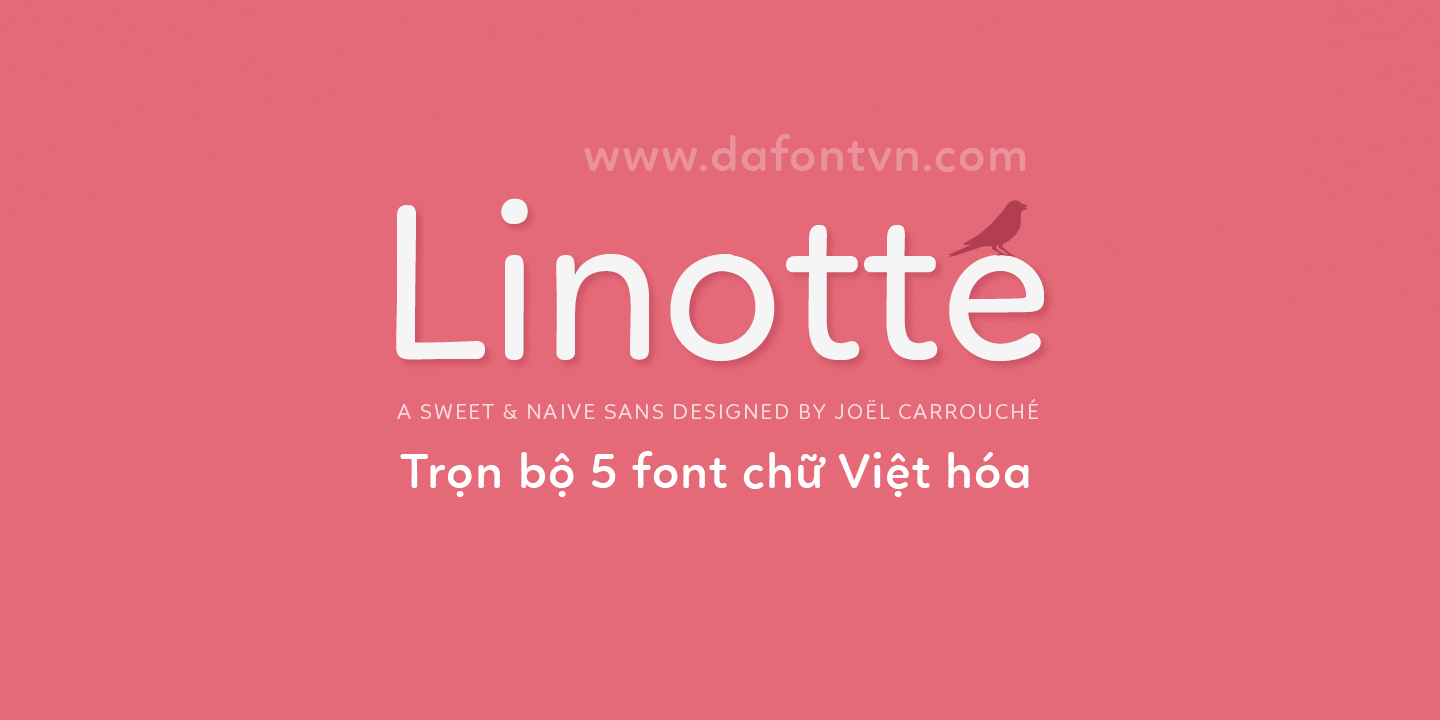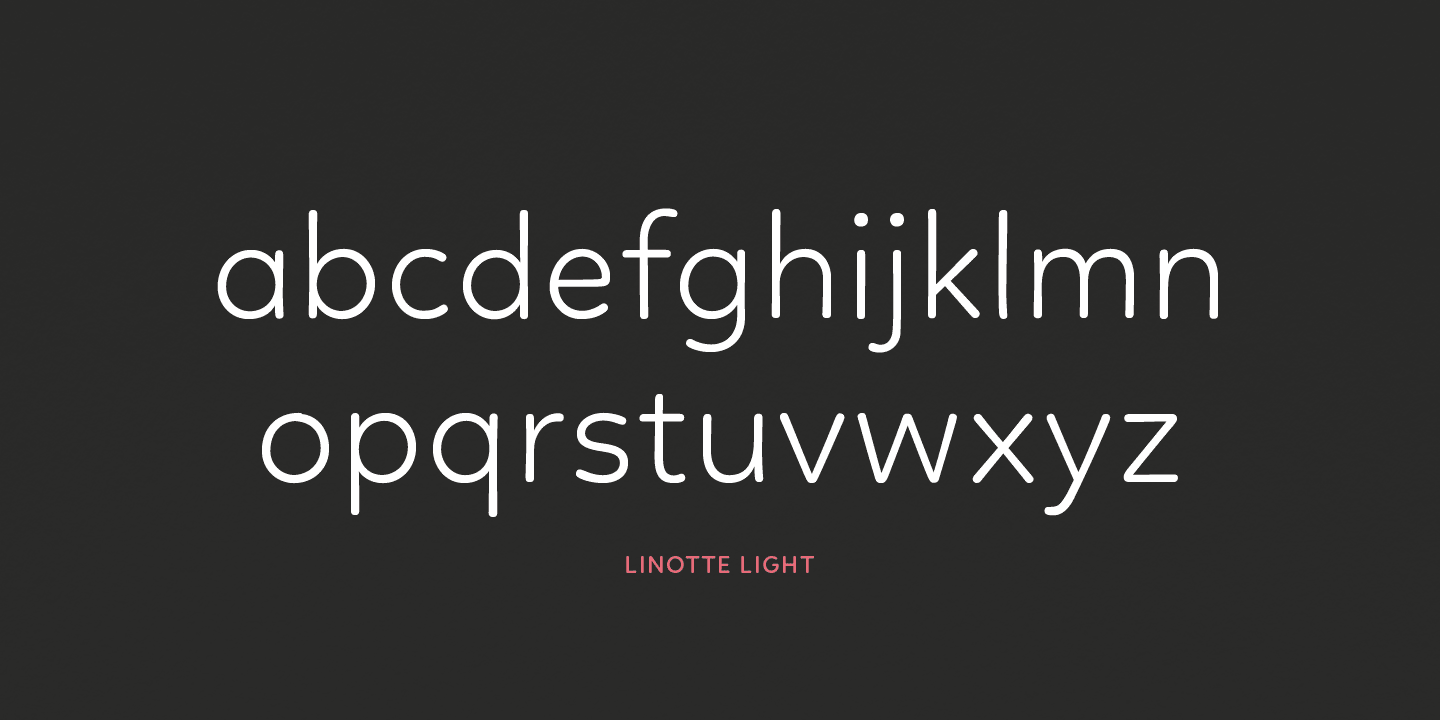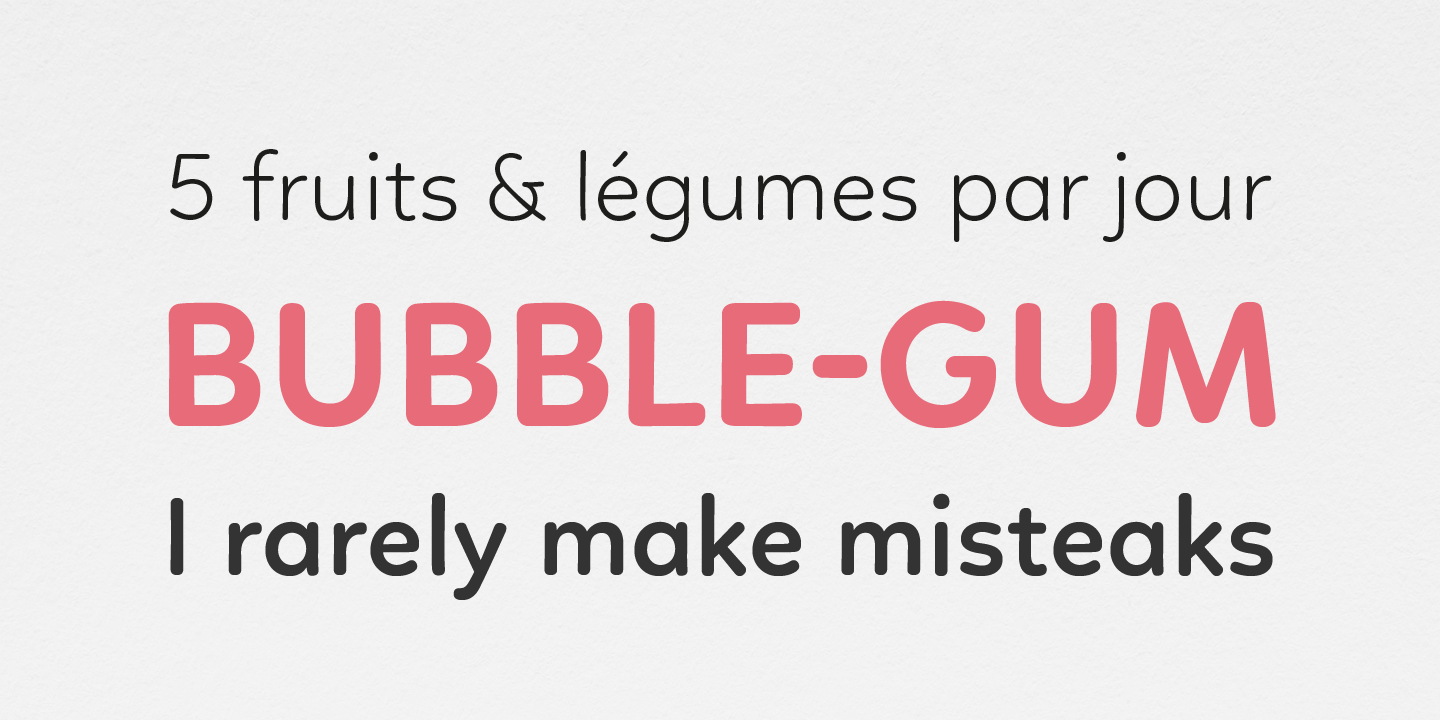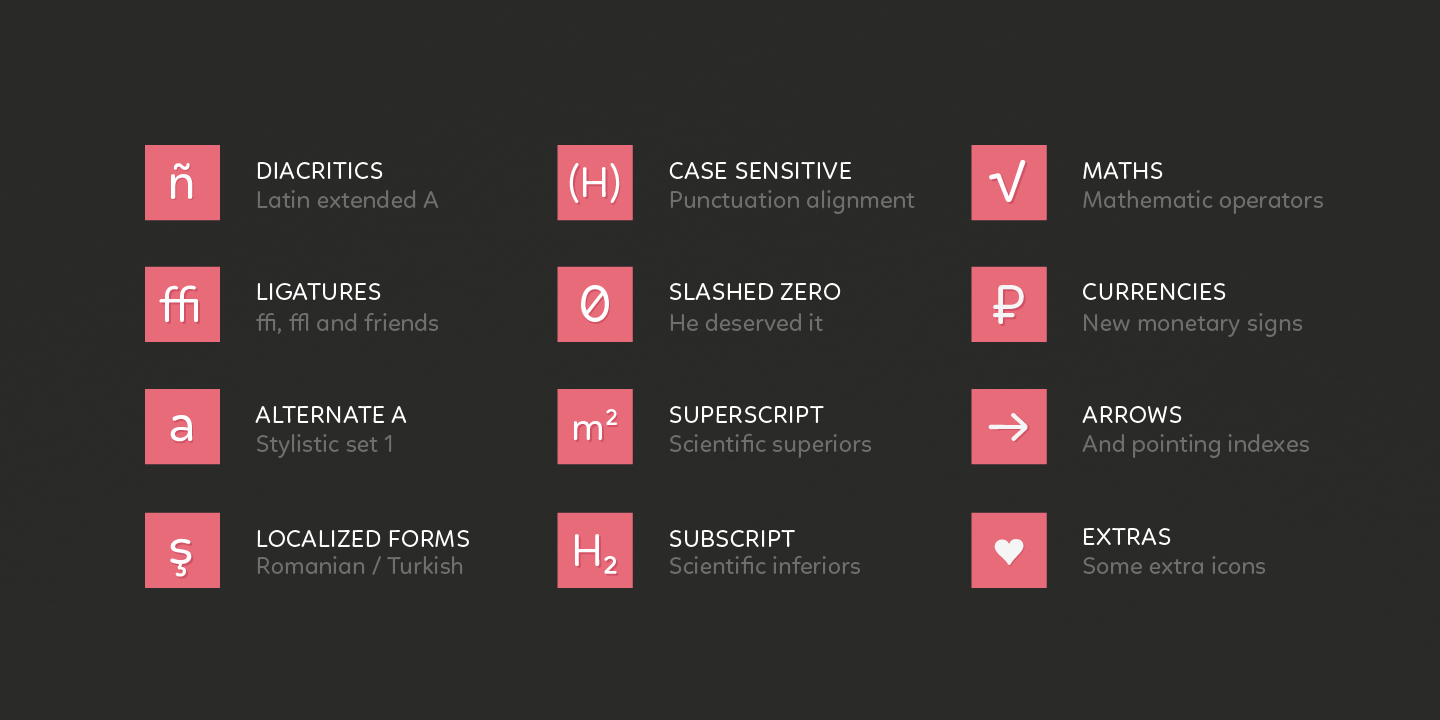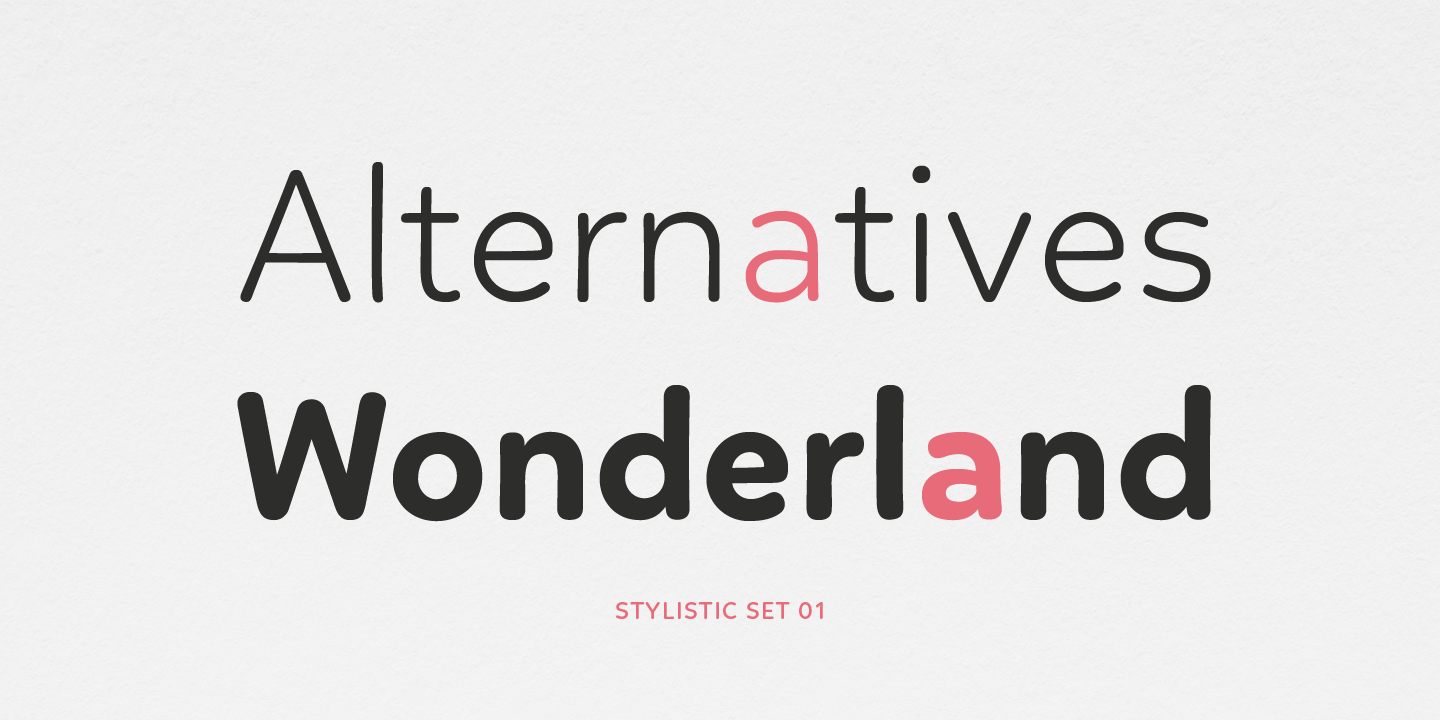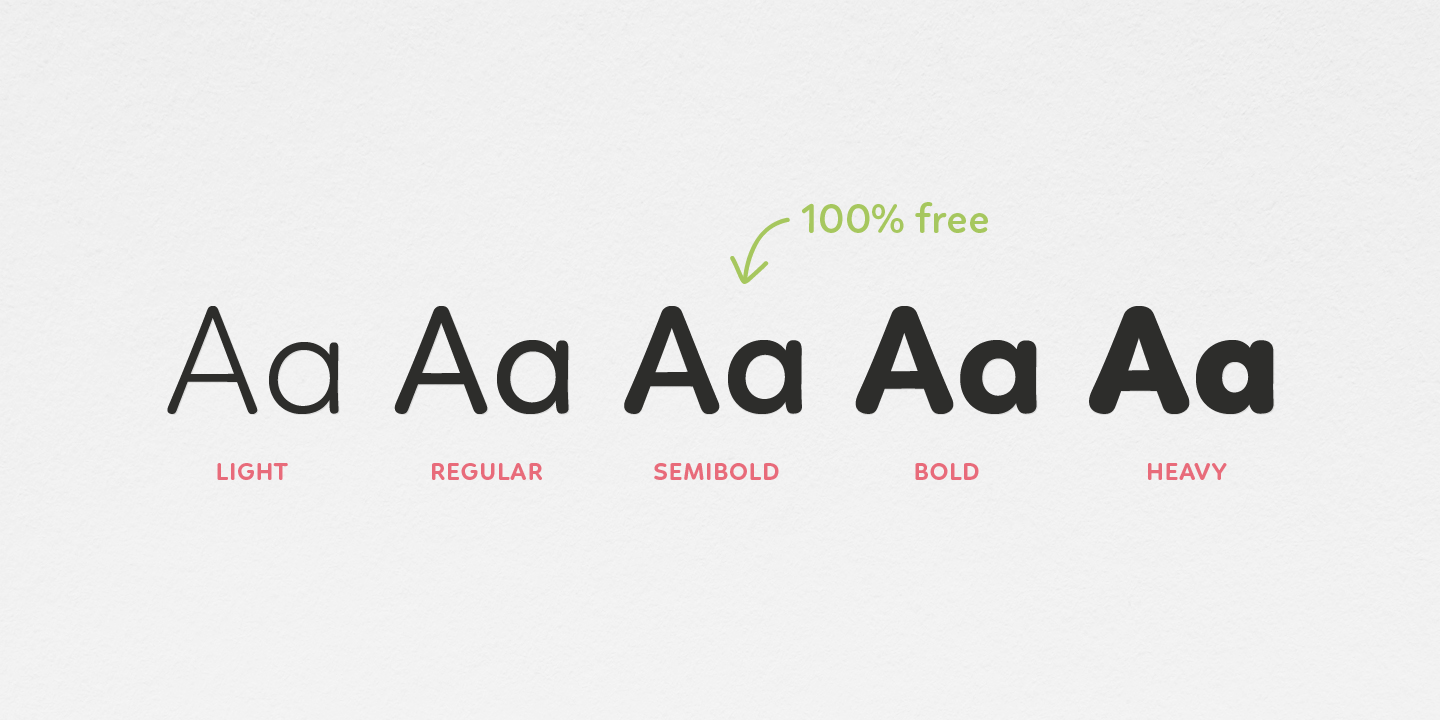
Linotte Rounded Sans Family Việt Hóa là bộ font ấn tượng với thiết kế các nét tròn trịa, được thiết kế bởi Joël Carrouché. Các điểm nhấn ấn tượng mang lại cho kiểu chữ một cái nhìn ấm áp, trong khi cấu trúc hình học vững chắc cho phép dễ đọc tốt trong các văn bản dài và kích thước nhỏ.
Font chữ Linotte trọn bộ 5 font được cung cấp ở định dạng OpenType, bao gồm các dấu phụ cho hầu hết các ngôn ngữ Châu Âu, một tập hợp các mũi tên và biểu tượng và một loạt các tính năng nâng cao như thay thế kiểu cách, biểu mẫu phân biệt chữ hoa chữ thường, chỉ số trên, v.v.